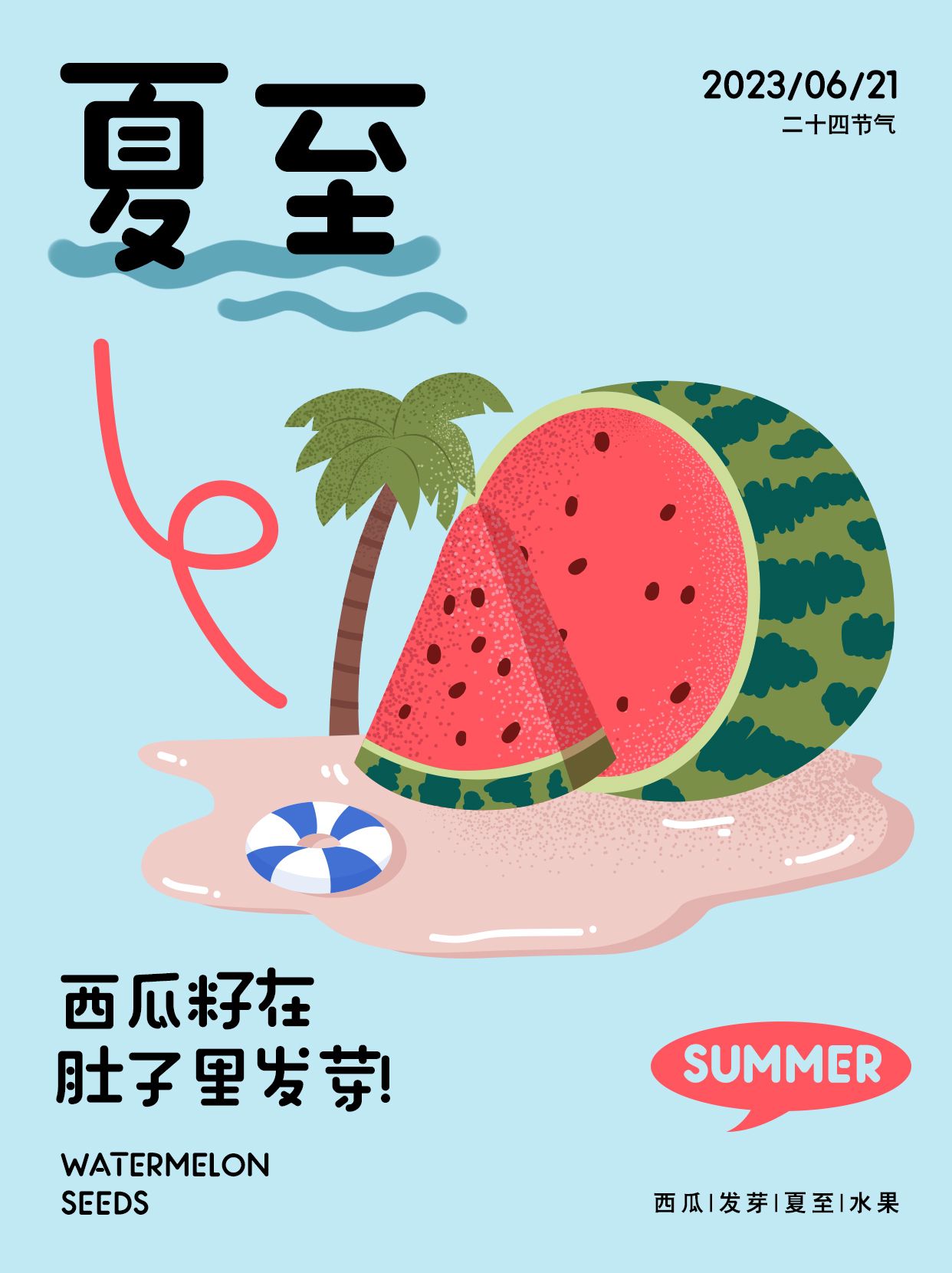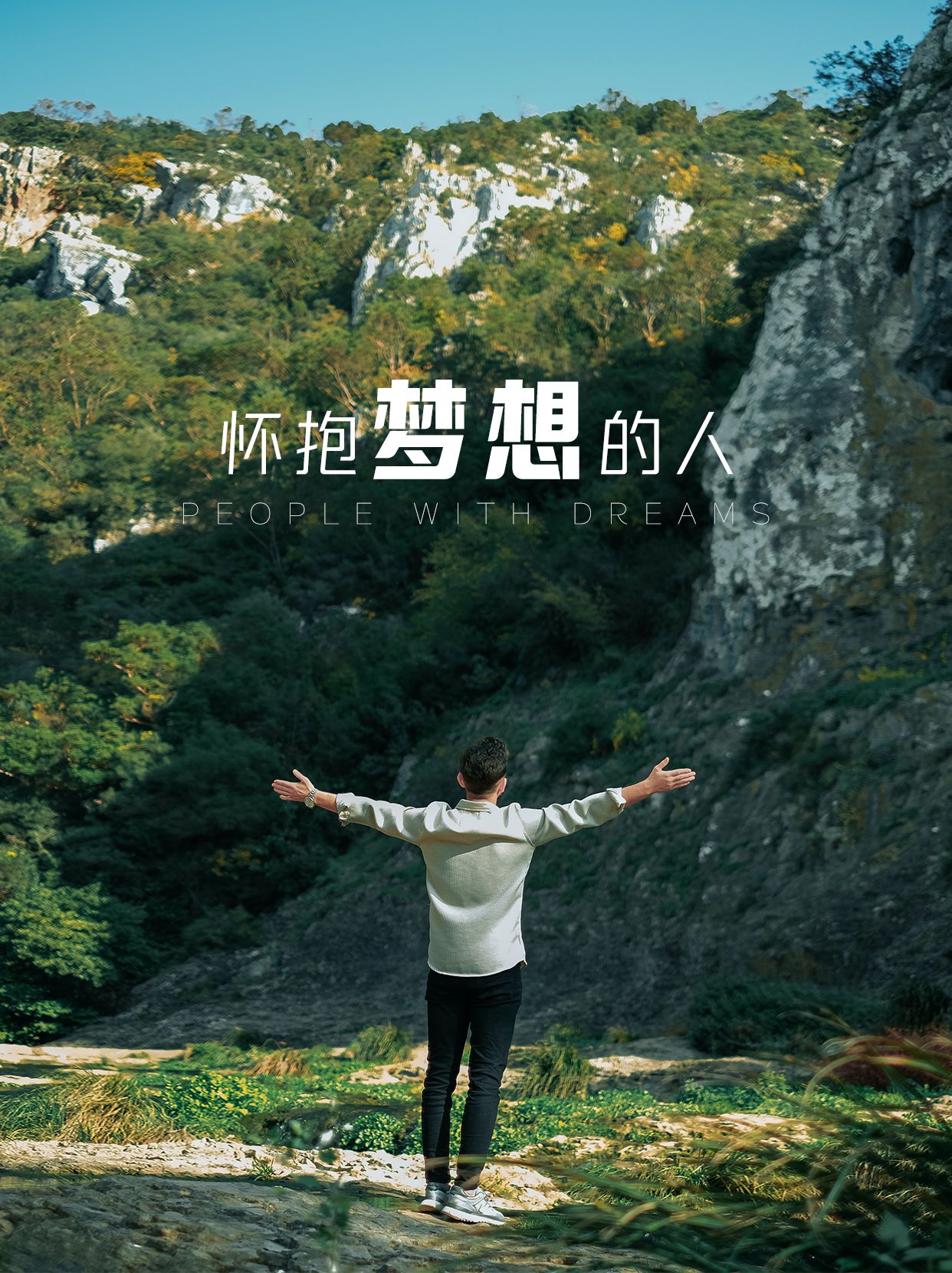
美食设计中的字体艺术:让味蕾与视觉共舞
在美食的世界里,每一道佳肴都是视觉与味觉的双重盛宴,而恰当的字体选择,则能为这份享受增添一抹独特的艺术气息。今天,就让我们一起探索几款专为美食领域设计的字体,让文字也成为餐桌上的一道亮丽风景线。
在美食的视觉盛宴中,字体选择尤为关键。造字侠郝刚快乐简 微黑,以其活泼灵动的线条,为美食设计注入无限活力,让每一道佳肴都仿佛跃然纸上,生动诱人。其简约而不失力度的风格,清晰传达美食的精髓,既经典又时尚。两者结合,无论是菜单设计、海报制作还是品牌标识,都能完美展现美食的魅力,让食客在享受美味之前,先被这份视觉上的艺术所打动。
在美食的创意舞台上,励字小桃气简繁 大圆以其甜美细腻的笔触,为每一道佳肴披上了一层梦幻的纱幔,让美食不仅触动味蕾,更触动心灵。励字小桃气简繁 大圆其圆润饱满的形态,赋予文字以温暖和亲和力,让人一眼就能感受到食物带来的幸福感。两者在美食设计中的巧妙结合,不仅提升了整体的视觉美感,更让美食故事跃然纸上,引人入胜。无论是菜单排版还是品牌宣传,它们都是不可多得的选择。
在美食的视觉盛宴中,励字造梦简 中粗以其独特的梦幻风格脱颖而出。其圆润而富有弹性的线条,如同轻盈的云朵,温柔地包裹着每一个字,为美食增添了几分梦幻与浪漫。无论是餐厅菜单的精致排版,还是美食宣传海报的创意设计,励字造梦简 中粗都能完美融合,让文字与美食共同编织出一个个令人向往的味觉梦境,引领食客踏上一场难忘的味蕾之旅。
励字逆反差圆舞简 超级黑以其独特的反差美感,与超级黑的稳重气质完美融合,为美食设计带来全新视觉冲击。励字逆反差圆舞简 超级黑的圆润线条与强烈对比的笔画,形成鲜明反差,既展现了美食的柔和细腻,又不失其独特个性。这种搭配在菜单设计、品牌包装中尤为抢眼,让每一道佳肴都仿佛拥有了独特的语言,讲述着属于自己的美味故事。
在美食设计中,选择一款合适的字体,就像是为美食添加了一道独特的调味料。它能够让美食的魅力更加凸显,让食客在品尝之前就能感受到满满的期待与惊喜。以上几款字体推荐,希望能为您的美食设计带来灵感与启发。